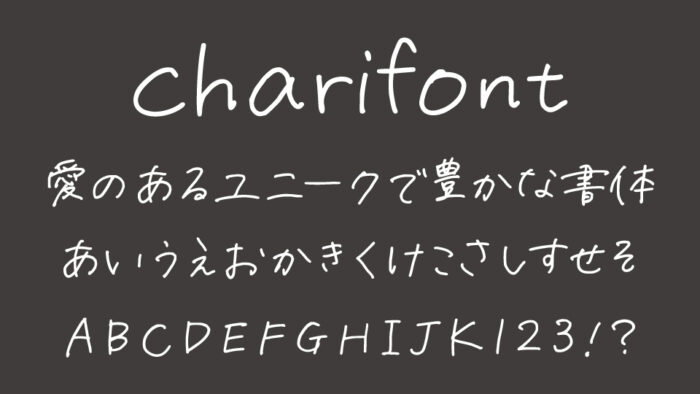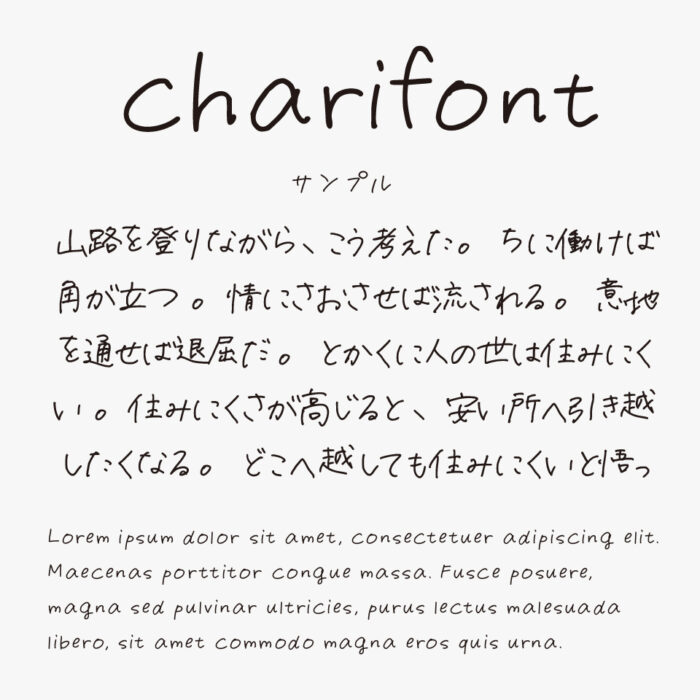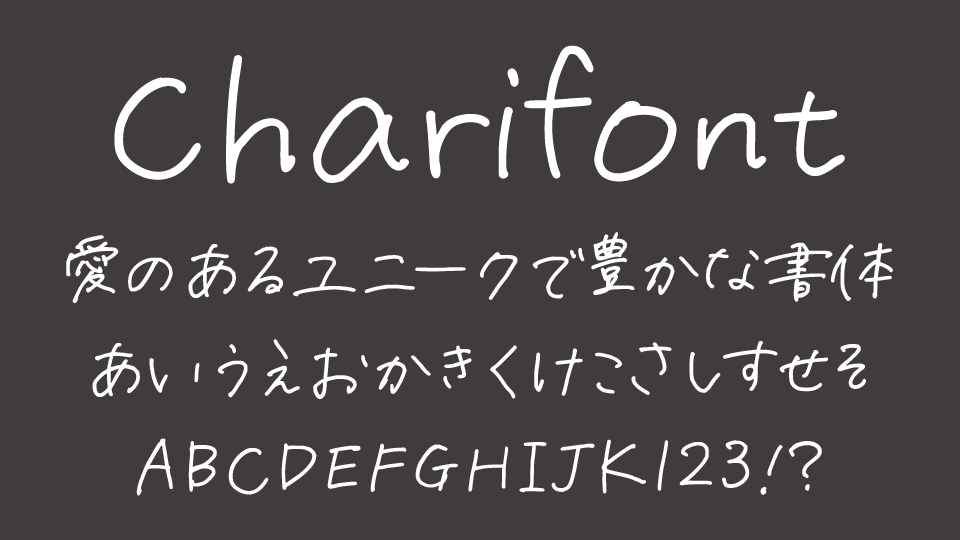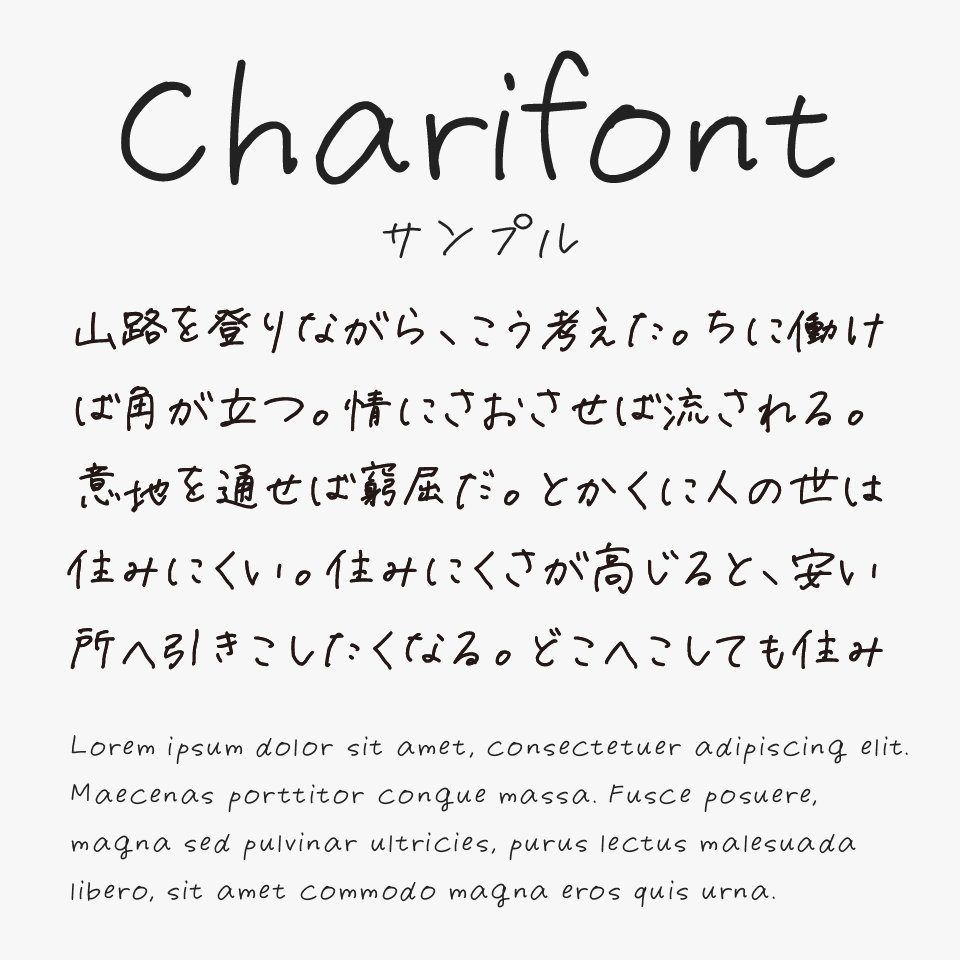
charifont
charifontは、リラックスして書かれたようなやさしさと、すこしラフな線のやわらかさのある手書きフォントです。
ボールペンで書いたようなかすれや揺らぎがあり、ひと文字ごとに人の気配を感じさせるリアルな手書き感がとてもステキな手書き文字です。
全体に軽やかで、余白の取り方もほどよく、ゆるっとした雰囲気があり手紙風のコンテンツや子ども向けのタイトル、エッセイの見出しなどにもぴったりなフォントです。